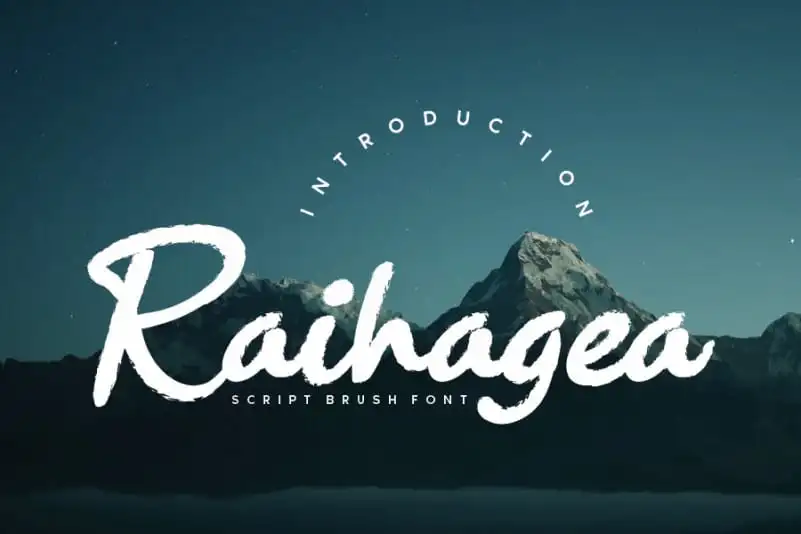
Raihagea Brush Font – Download Grátis
A fonte Raihagea Brush é uma escolha perfeita para designers buscando trazer um toque delicado e único aos seus projetos digitais. Escrevendo à mão, esta fonte apresenta um estilo versátil que vai além de simples texto; ela pode transformar qualquer design em algo singularmente encantador. Ideal tanto para criações gráficas quanto para o conteúdo digital, Raihagea Brush oferece uma infinidade de maneiras de usar sua elegância natural. Seja você criando aconchegantes efeitos visuais ou adotando um formato moderno e minimalista, este design irá tornar seu trabalho ainda mais especial. Com suas nuances delicadas e linhas fluidas, Raihagea Brush é perfeito para aquelas propostas que buscam uma sensação de conforto e confiança nas páginas digitais. Seja em um cartão de crédito, em uma capa de livro ou até mesmo em uma imagem de perfil do LinkedIn, este é o elemento ideal para tornar seu design ainda mais personalizado e atraente.